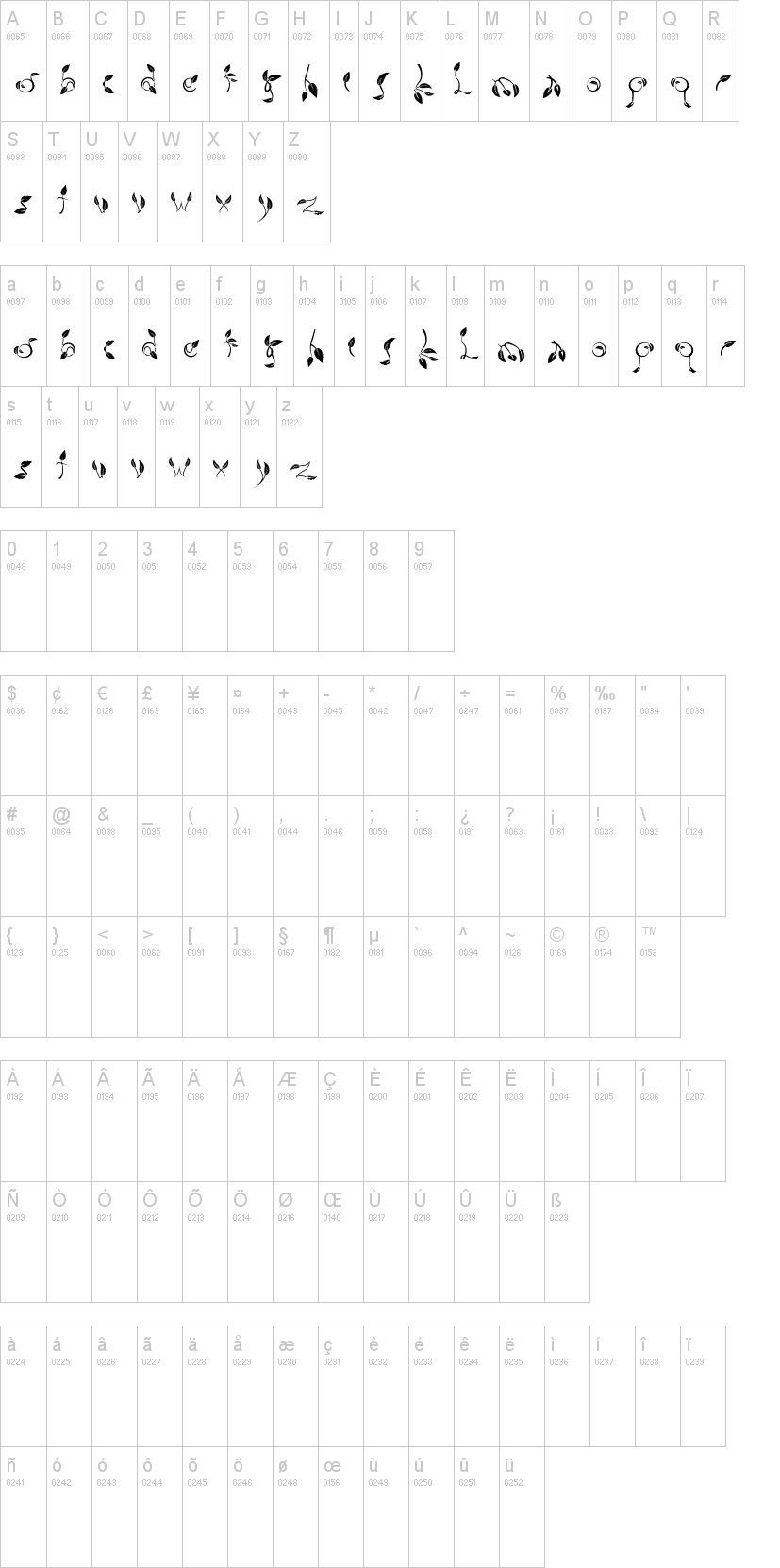
Dedaun
Dedaun是一种美丽而现代的字体,适用于涵盖多种语言的设计项目。它由马来西亚的设计师Hafizul Hakim创作,以大自然中的树叶为灵感,因此得名为“Dedaun”,意为“叶子”(在马来语中)。它具有流畅的曲线和清晰的线条,字母间距离适中,非常易读。 Dedaun字体家族包括三种字重:普通、粗体和斜体。字体适用于多种设计项目,包括海报、标志、书籍、博客和网站设计等。字体的特点是具有现代感和自然感,使得它非常适合与自然主题和品牌搭配使用。 总的来说,Dedaun是一种优雅、现代和多功能的字体,适用于多种语言和设计项目。
Dedaun是一款非常不错的手写艺术字体,具有很好的视觉感,适合于文化类的宣传设计、商业类品牌的广告和产品包装设计以及个性化文字排版等较多场景。